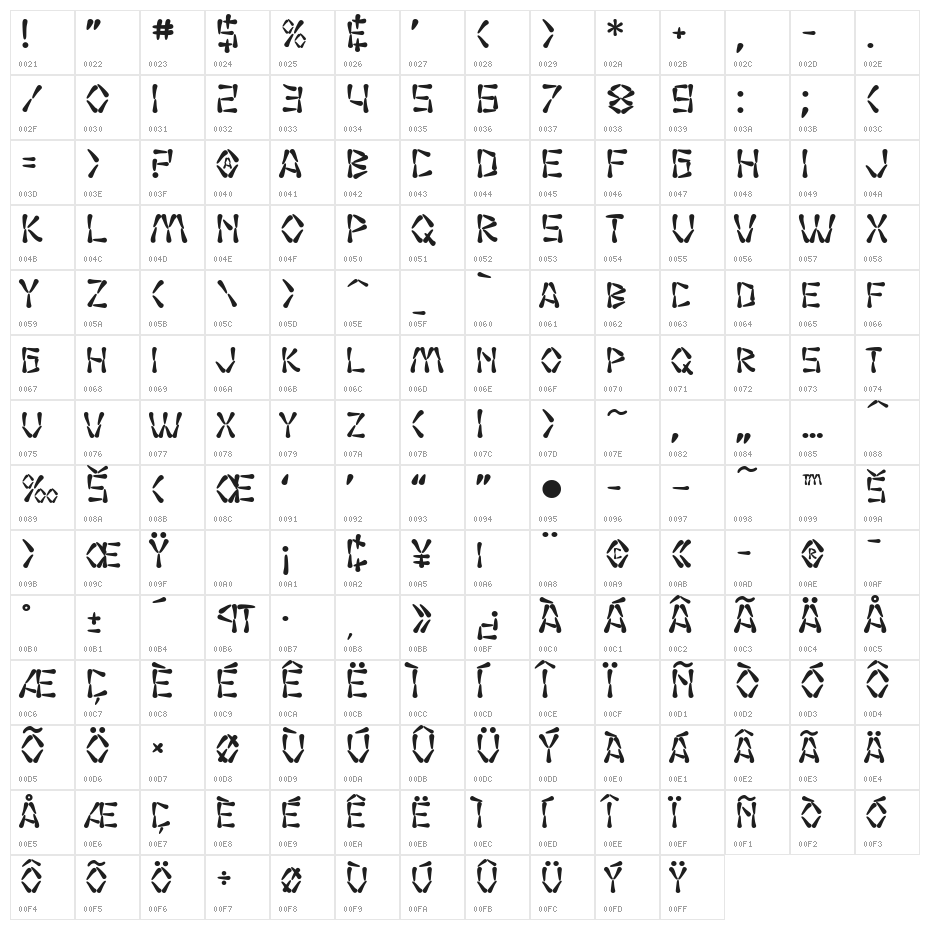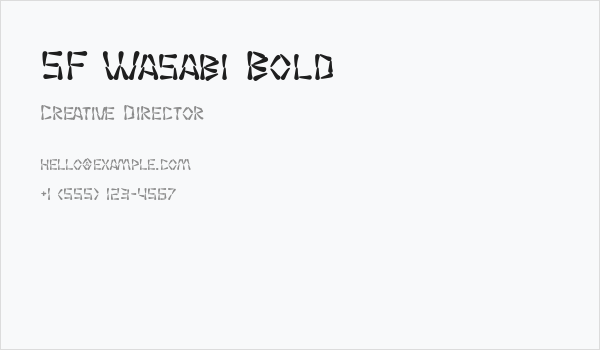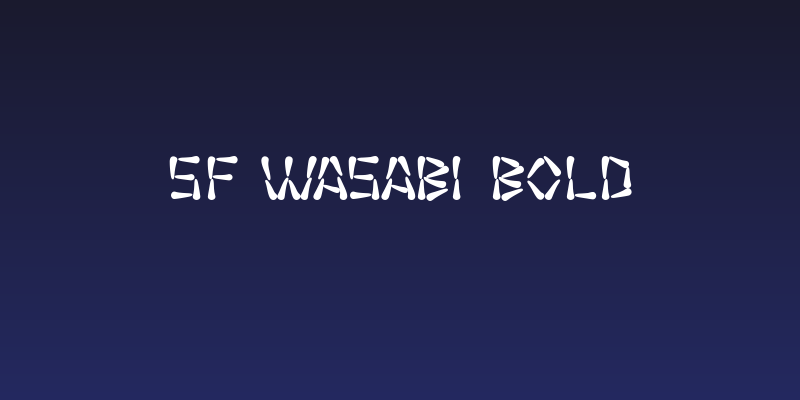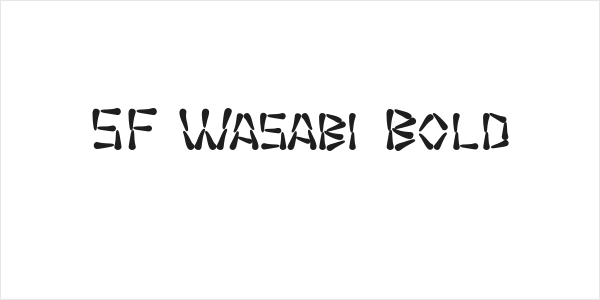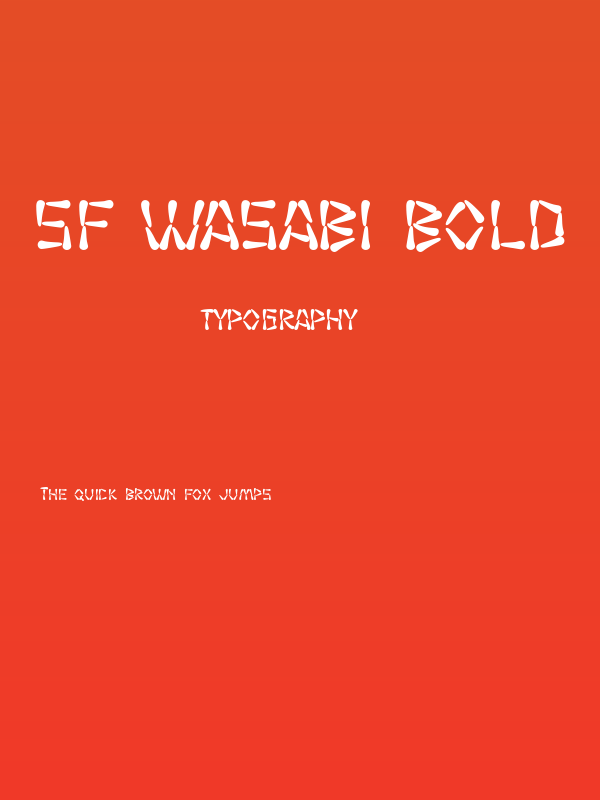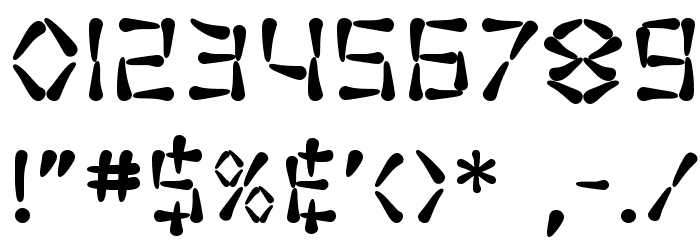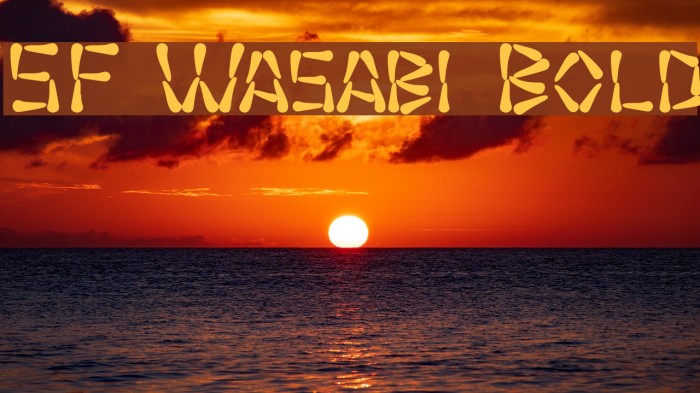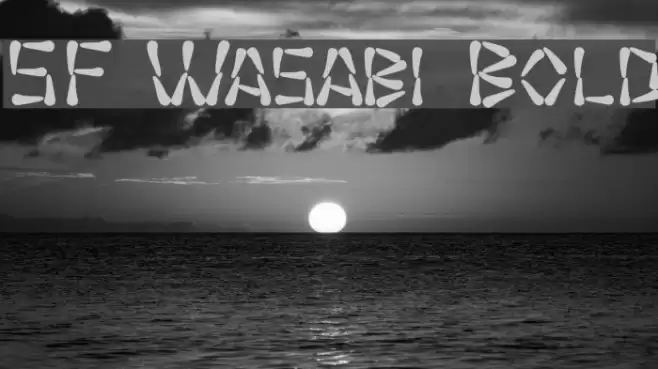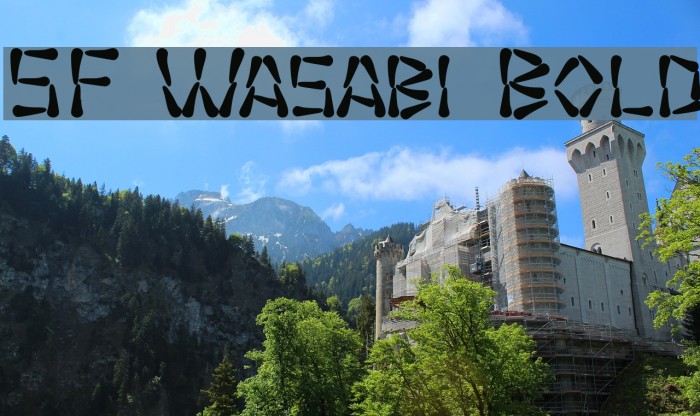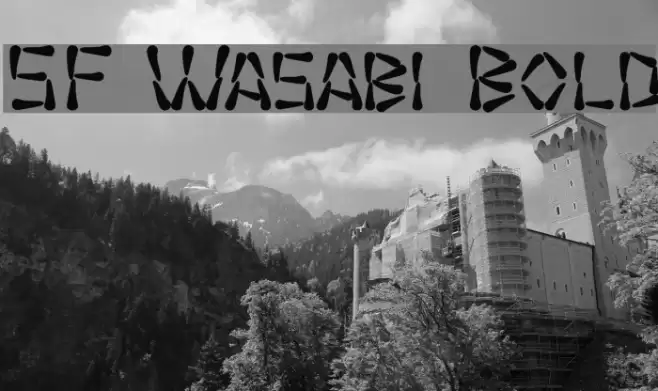
SF Wasabi Bold Font
| Projetos propostos | Ideal for creative projects such as children's books, playful branding, event posters, and artistic packaging designs. |